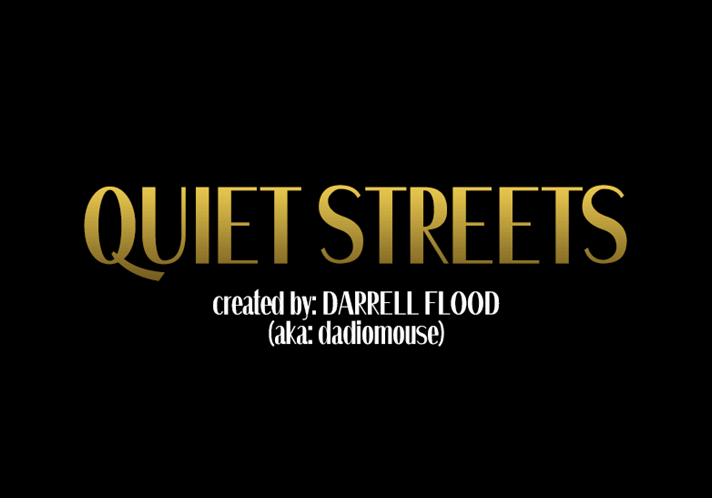
Introduzimos Quiet Streets Font, uma elegante tipografia sans-serif ideal para títulos e logomarcas. Esta fonte é muito limpa e ampla, perfeitamente adequada para logos, círculos de título e design de tipo. Quiet Streets foi criado por Darrell Flood. Este tipo de sans serif minimalista e sofisticado inclui mais de 300 caracteres, tornando-o uma opção perfeita para projetos de arquitetura ou ilustração. Quiet Streets será um excelente complemento para muitas outras fontes, ajudando você a criar designs impecáveis. Idealmente, este tipo combinará maravilhosamente com outros recursos gráficos em seu próximo projeto.